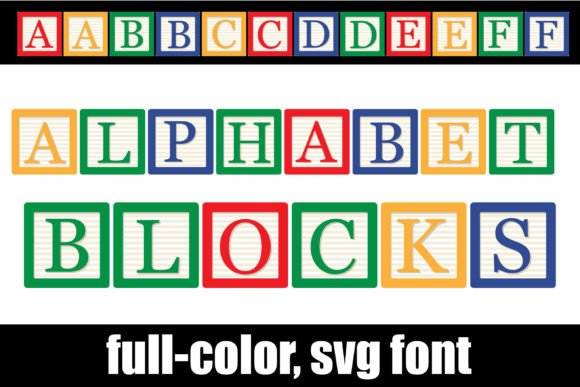
Alphabet Blocks
Jika anda sedang mencari aset berkualiti tinggi seperti Alphabet Blocks, pakej premium ini merupakan pilihan yang hebat untuk projek kreatif anda.
Dicipta dengan ketepatan, Alphabet Blocks menyediakan vektor yang bersih, tipografi yang licin dan lesen komersial untuk ketenangan fikiran.
Sama ada anda mencipta produk POD (Print on Demand), jemputan perkahwinan atau grafik media sosial, Alphabet Blocks amat bersesuaian.